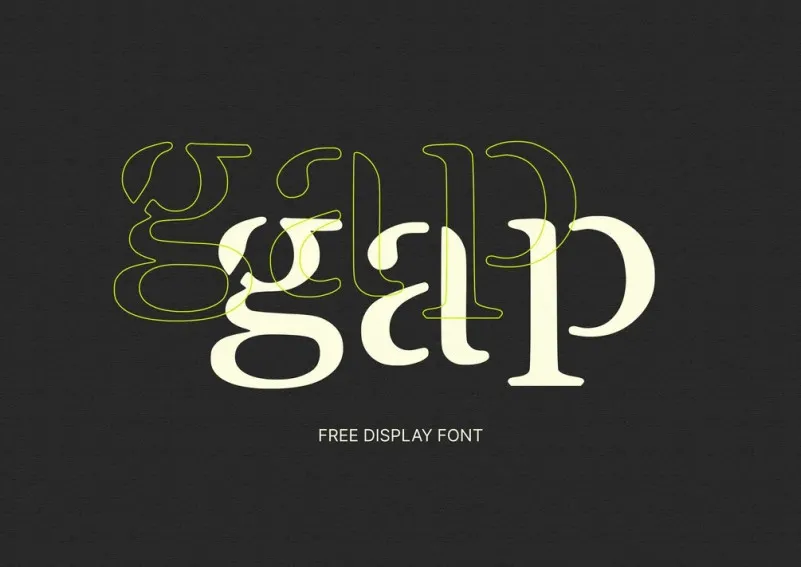
A fonte GAP Font é uma combinação fascinante entre um estilo moderno sofisticado e uma tipografia clássica. Desenvolvida por Cheska Ocampo, essa fonte apresenta caracteres minimalistas que permitem uma edição simples e fluida dos designs. Suas linhas leves e puras são perfeitas para criar marcas de marca, logotipos, convites de casamento e cartões pessoais. Além disso, ela pode ser utilizada em projetos que buscam um equilíbrio elegante entre a modernidade e o charme do clássico. Ideal tanto para aqueles que querem dar um toque sofisticado aos seus trabalhos como para designers que valorizam uma tipografia fácil de editar sem perder a essência gráfica.